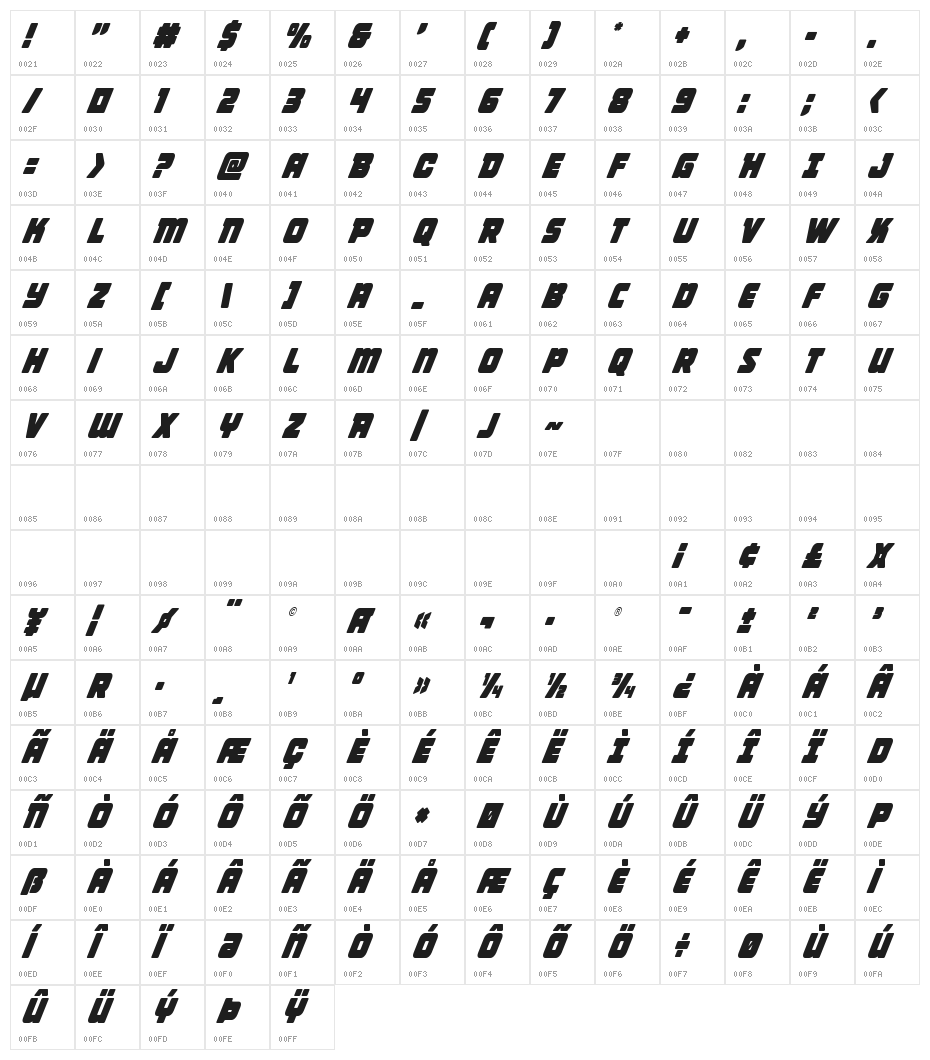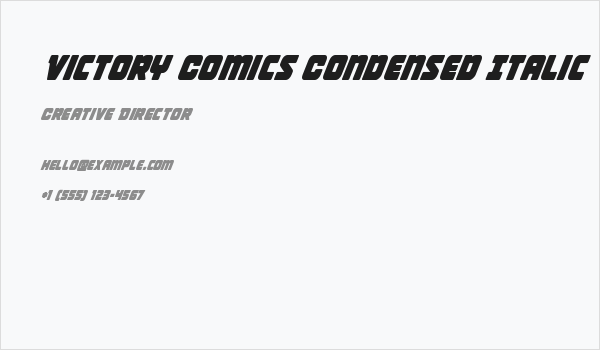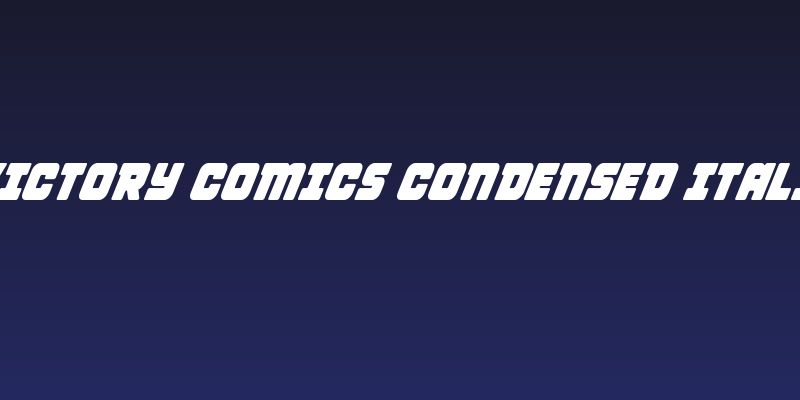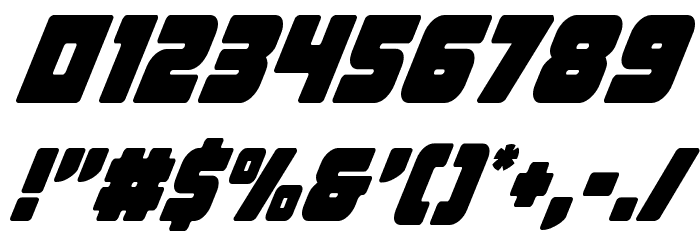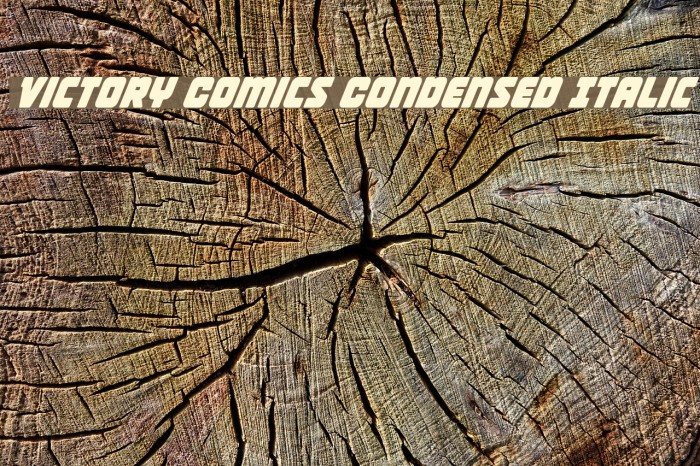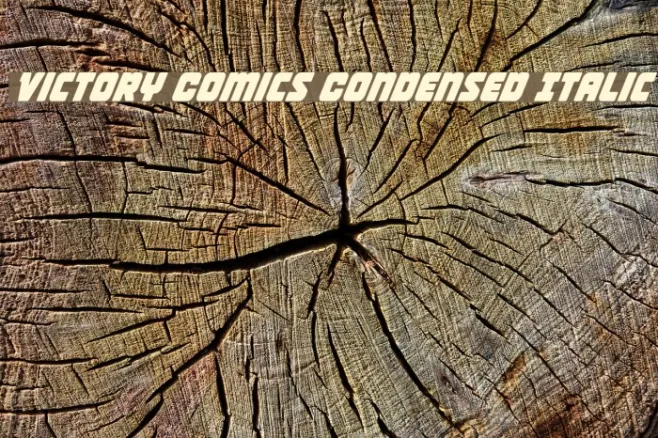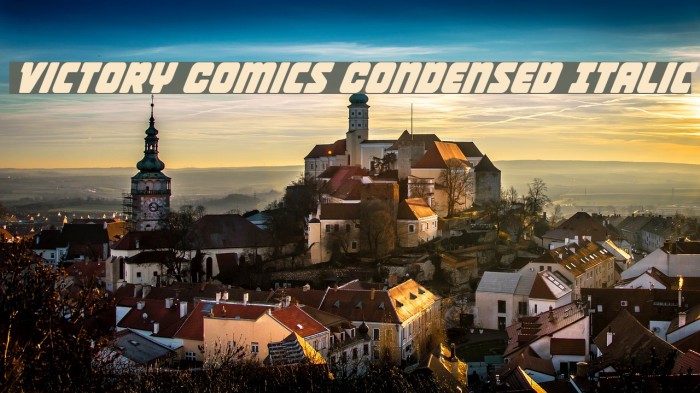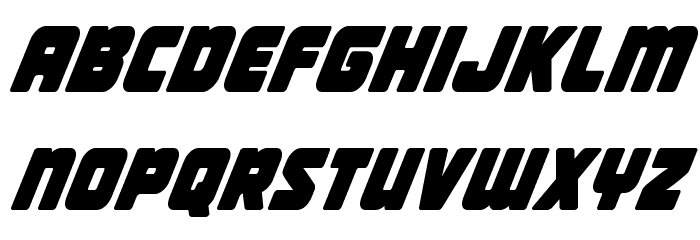
Victory Comics Condensed Italic Font
| Proyectos propuestos | Ideal for comic books, graphic novels, posters, and branding that requires a bold and energetic look. |